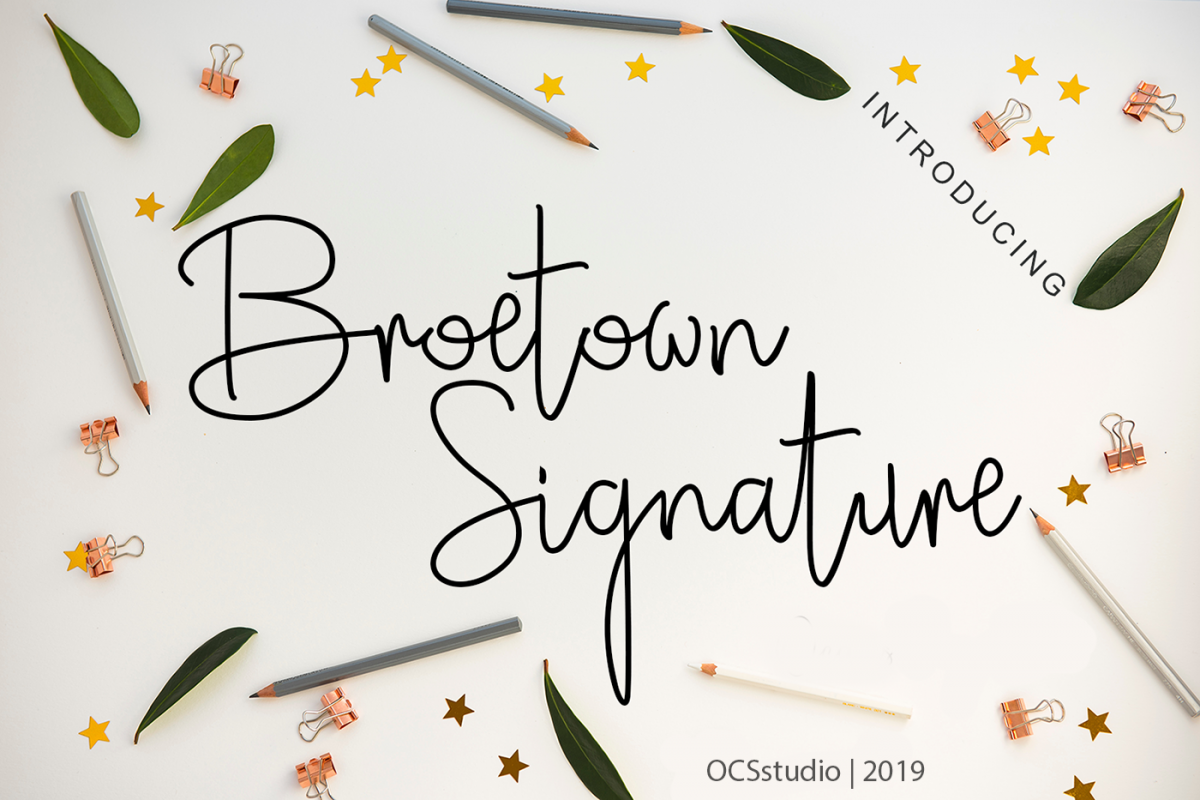
Broetown Signature
Memperkenalkan Broetown Signature , tulisan tangan penuh gaya dengan gaya khas. Fon skrip yang indah ini menawarkan sentuhan pribadi Anda pada proyek seni terbaru Anda dengan tampilan elegan, berkelas dan modern.
Broetown Signature menawarkan tipografi yang indah akan cocok untuk berbagai proyek seperti logo & branding, undangan, alat tulis, desain pernikahan, posting media sosial, iklan, kemasan produk, desain produk, label, fotografi, tanda air , acara khusus atau apa pun yang membutuhkan selera tulisan tangan .